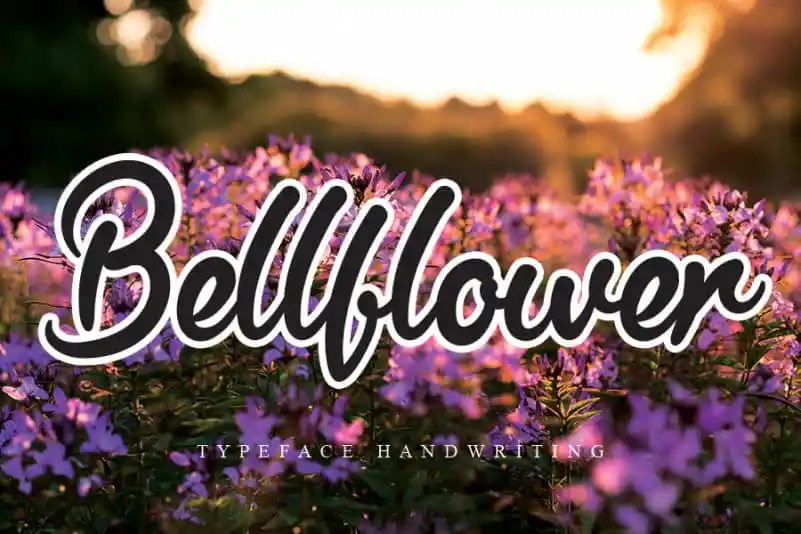
Bellflower Handwritten Font – Download Grátis
A Bellflower Handwritten Font é uma elegante escolha para quem busca estilo autêntico no design digital. Inspirada na escrita manuscrita real, ela traz consigo um charme inconfundível que se adequa perfeitamente a vários projetos gráficos. Seja para criar cartões de boas-vindas surpreendentes e delicados, arte de registro de uma beleza única ou postagens sociais irresistivelmente atrativas, esta fonte manuscrita oferece flexibilidade para transformar qualquer layout em algo realmente especial. Com seu aspecto cuidadosamente elaborado, a Bellflower Handwritten Font é ideal para quem deseja dar um toque romântico e artesanal às suas criações digitais. É perfeita para aqueles que buscam criar mensagens pessoais e memoráveis em seus projetos de design. Além disso, sua versatilidade permite que você encontre a fonte certa para cada projeto, seja para cartões de aniversário ou até mesmo para o desenvolvimento de um site web moderno. Tornando-se uma aliada valiosa no seu armário de ferramentas gráficas, a Bellflower Handwritten Font oferece tanto funcionalidade quanto beleza. Ela é perfeita para quem busca criar arte digital única e emocionante, que ressoa com verdadeira emoção e personalidade.